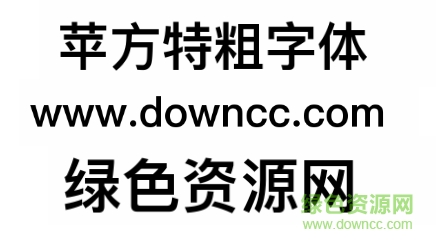
蘋方特粗字體是一款加粗后的蘋方字體,端正大氣,適合電子閱讀和各類平面設(shè)計,需要的朋友歡迎來綠色資源網(wǎng)免費下載!
蘋方特粗字體來自于蘋果系統(tǒng)中的一款藝術(shù)字體,加粗的設(shè)計讓文字顯得更加出眾有標識性,在排版印刷、網(wǎng)頁編輯、海報設(shè)計、廣告創(chuàng)意等領(lǐng)域!